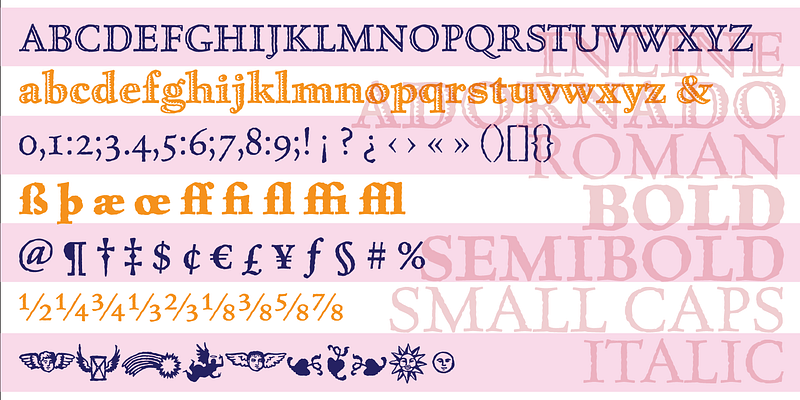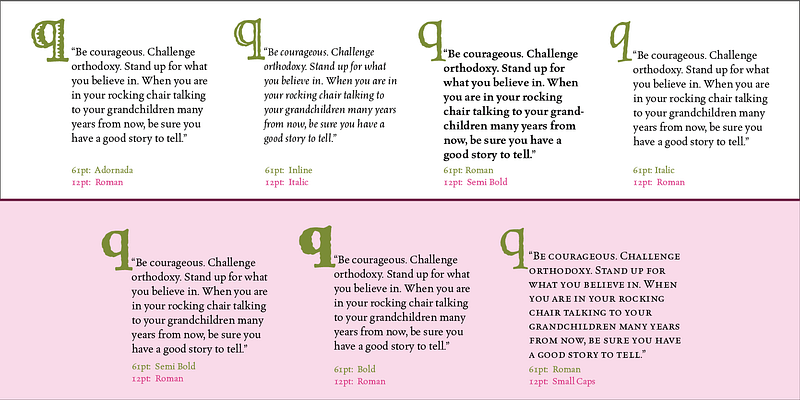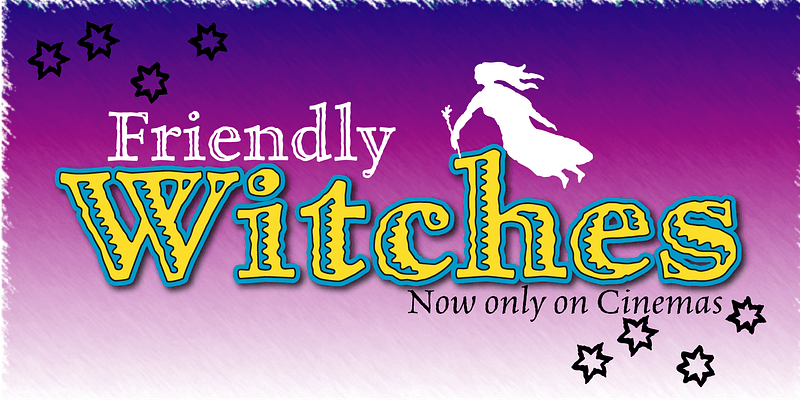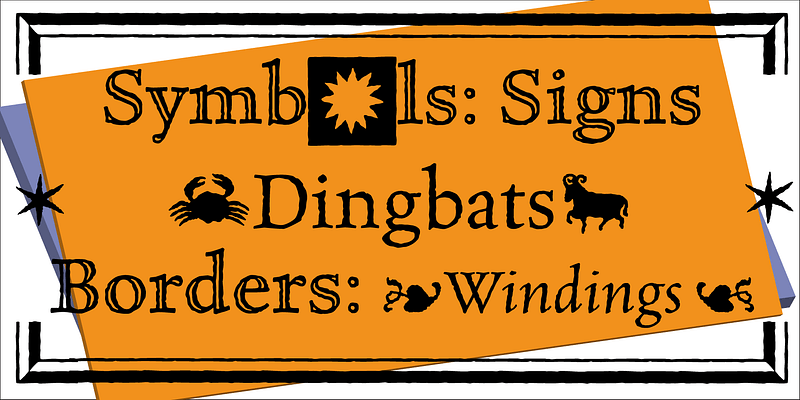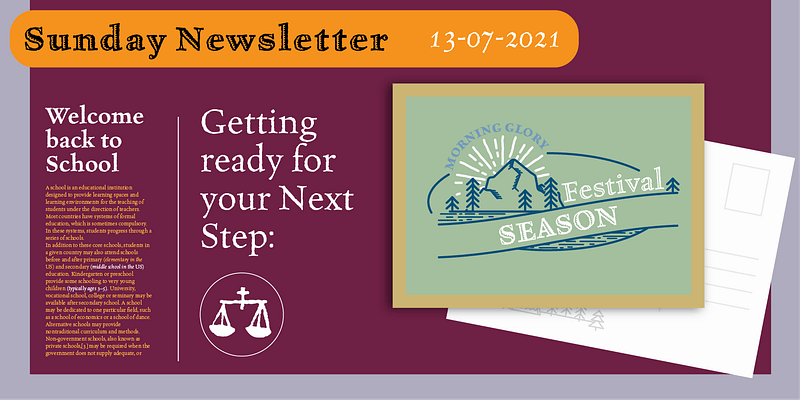
Mark van Bronkhorst diseñó MVB Celestia Antiqua en una época en la que la oferta de fuentes era limitada. El diseño se caracterizaba por el uso excesivo de los pocos tipos de letra que venían con las impresoras láser. Un tipo de letra rústico, que recuerda la aspereza e irregularidad de la impresión predigital, fue una respuesta a la fría nitidez de la autoedición. MVB Celestia Antiqua se mantiene entre un gran grupo de fuentes serif “desgastadas”, en parte debido al tamaño de la familia: tres grosores, versalitas, cursiva y dos estilos de título. Pero también tiene éxito porque simplemente está bien dibujada, los contornos solo son tan ásperos como es necesario, lo que permite que el texto sea de cualquier tamaño, grande o pequeño.